Points forts de la fonderie Paulo Goode.
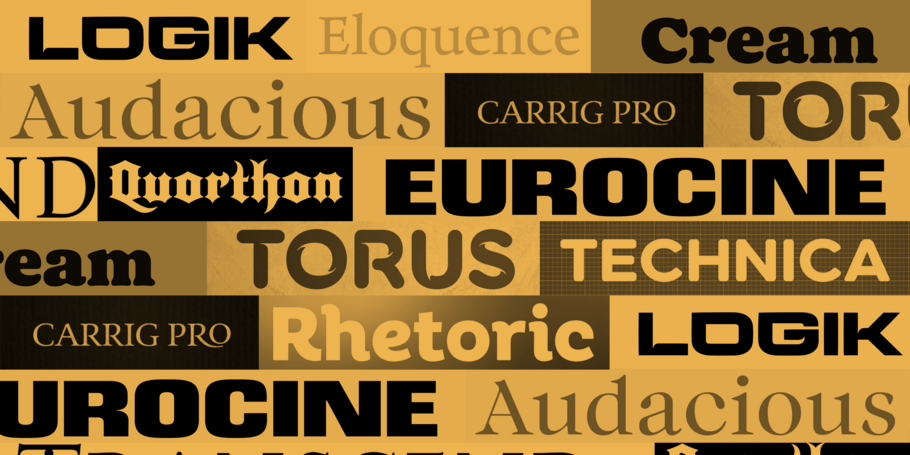
Paulo Goode.
Paulo Goode est un designer indépendant basé en Irlande, qui a adopté la création de caractères typographiques après une carrière de 30 ans dans l’illustration, le design graphique et le développement de sites web. Créée en 2016, sa fonderie a déjà publié plusieurs designs populaires, et ses polices ont été utilisées sur des emballages, dans des publicités pour des marques, pour des couvertures de livres et même dans des jeux vidéo. Les designs de Paulo consistent principalement en polices destinées aux supports commerciaux et à l’identité visuelle de marque, c’est-à-dire exactement le genre de typographie qu’il recherchait lorsqu’il était designer graphique. Il est spécialisé dans la création de types polyvalents bourrés de fonctionnalités qui apportent une valeur exceptionnelle à leurs utilisateurs.
Cream
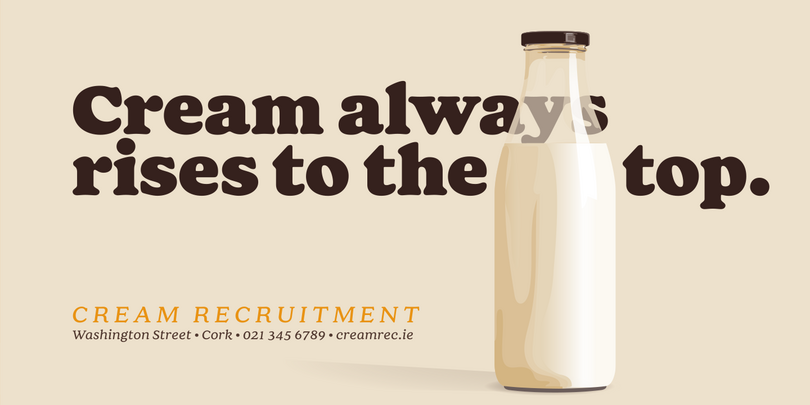
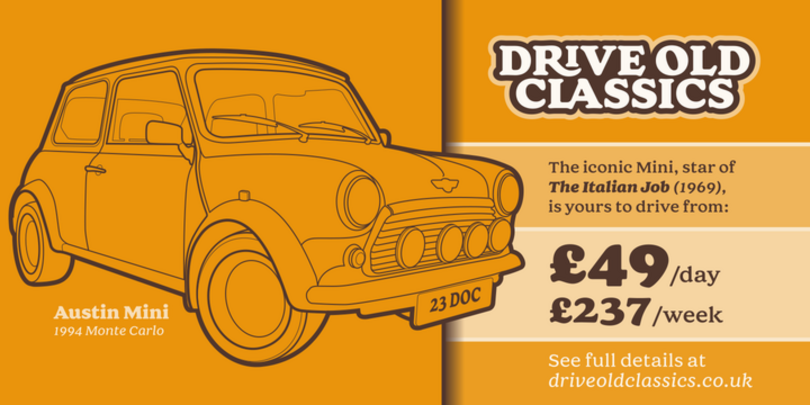
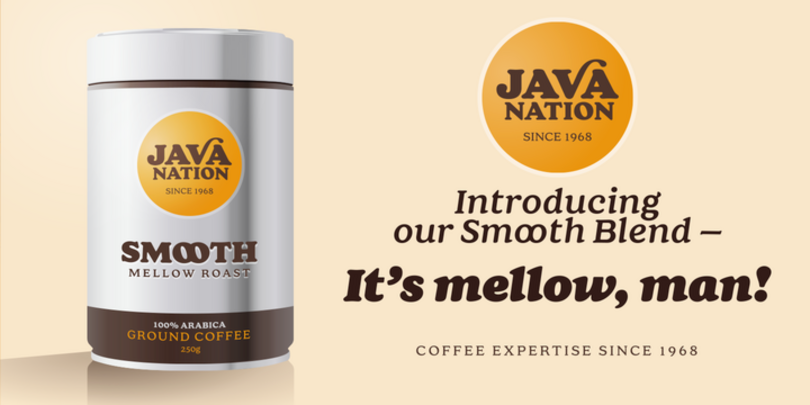
Cream est une police rétro douce à empattement, dotée de nombreuses alternatives et ligatures décoratives qui enrichiront vos compositions typographiques de fioritures distinctives. Utilisés subtilement, ces ornements et combinaisons de glyphes ajouteront du style et de la personnalité à vos créations. Bien que Cream soit parfaite pour le titrage et l’identité visuelle de marque, sa gamme de graisses et sa lisibilité intrinsèque en font une famille de polices qui convient à la plupart des applications, de l’identité de marque au corps de texte. Elle inclut 12 fontes et un jeu de caractères complet qui couvre toutes les langues latines d’Europe.
Logik
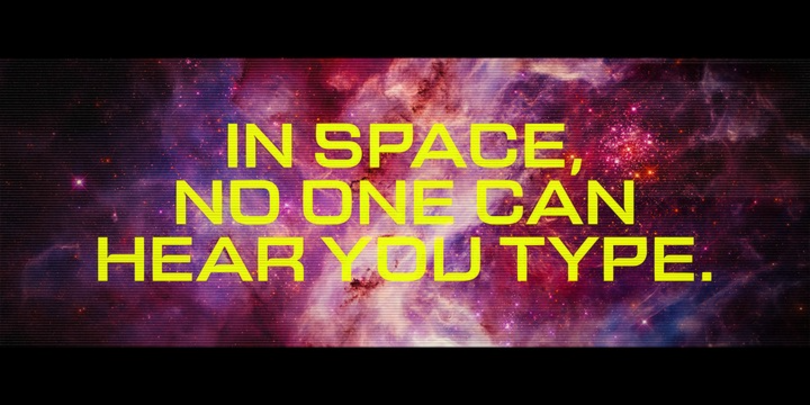
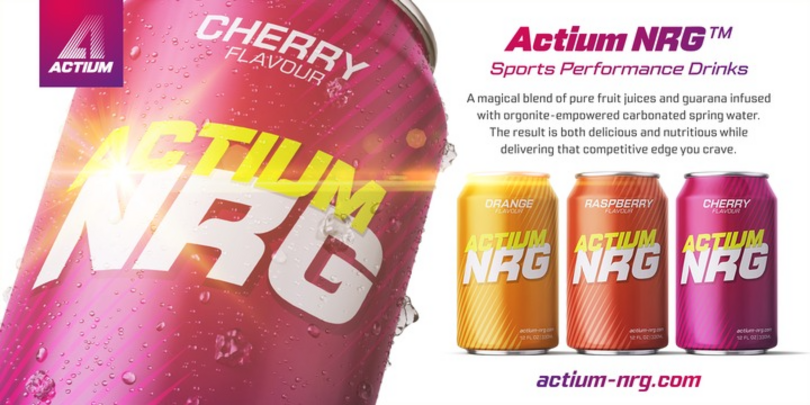
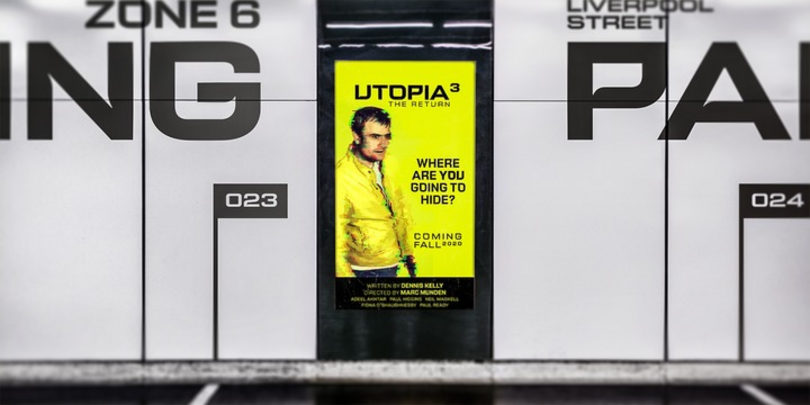
Logik est une police sans serif géométrique et futuriste. Sa personnalité est définie par des angles droits là où l’on attendrait plutôt des arrondis, ces contours nets conférant aux glyphes une certaine excentricité. Les pièges à encre gravés/stylisés bien évidés, alliés à des horizontales et à des verticales légèrement incurvées/effilées ajoutent une particularité à chaque forme de lettre. Ces subtilités se combinent pour donner à Logik une aura futuriste distinctive. Ce type est principalement utilisé pour les titres, les textes courts, l’identité de marque et les enseignes. Il s’avère idéal pour les titres de films et de livres ; c’est également une excellente option dans le domaine sportif ou des médias, ainsi que pour les projets typographiques dans l’univers du divertissement.
Carrig Pro
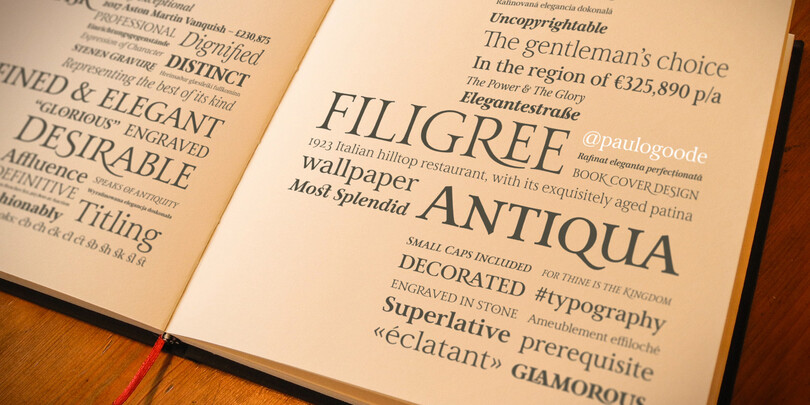
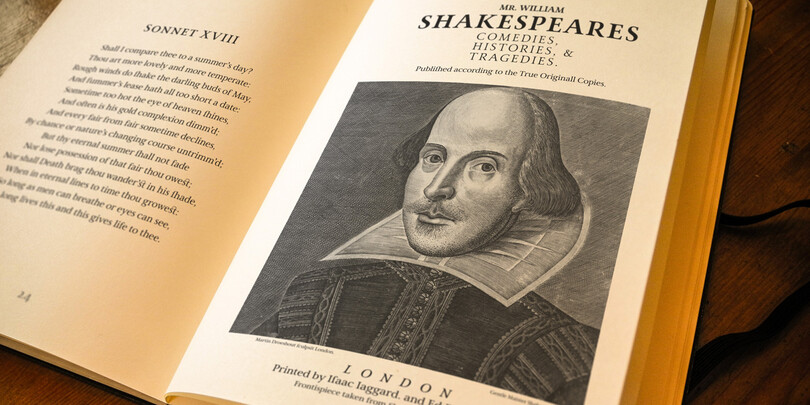
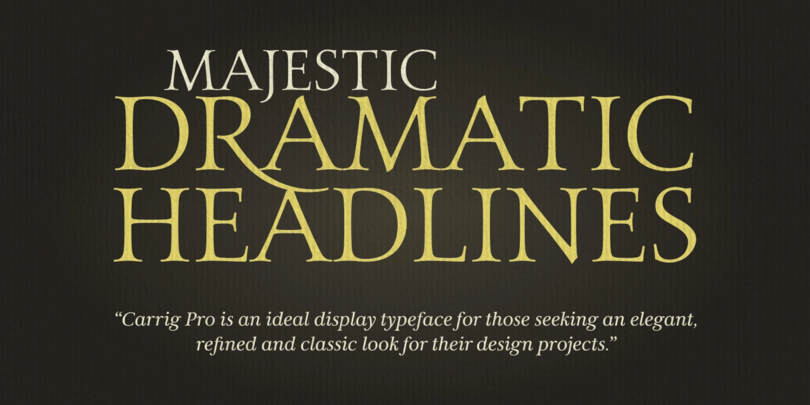
Carrig Pro est un type à empattement tout en raffinement et élégance. Classé dans la catégorie Antiqua, Carrig Pro est né de diverses influences allant des anciennes inscriptions romaines aux types de l’ère pré-moderne, ce qui lui confère son caractère si particulier. Carrig Pro est la police parfaite pour les designers cherchant à délivrer un message dans une esthétique distinctive et prestigieuse. Carrig Pro est une version étendue du type original Carrig. Elle possède de nombreuses fonctionnalités utiles pour les typographes, telles que de petites capitales faciles d’accès, des ligatures facultatives, des embellissements et des alternatives stylistiques, ainsi qu’un certain nombres de glyphes ornementaux.
Eponymous
Mécane dotée d’empattements imposants, bien découpés, Eponymous est une police slab polyvalente, stylée et contemporaine destinée à la création de logos et d’identités visuelles distinctives. Eponymous regorge de terminaisons en forme de boule et, sous des allures très rétro, elle offre bon nombre de fonctionnalités OpenType telles que des alternatives stylistiques, ainsi qu’un jeu complet de petites capitales incluant des signes diacritiques et des chiffres.
Transcend
Le type Transcend a été spécifiquement conçu pour le titrage et l’identité de marque. Cette police à 8 fontes uniquement composée de capitales est généreusement dotée de fonctionnalités OpenType, notamment des ligatures facultatives et des alternatives qui, lorsqu’elles sont employées subtilement, confèrent une note distinctive à la typographie des titres. Cette police est une émanation du type Carrig original créé par le designer. Elle est embellie par des lignes pures et des empattements nets, des pièges à encre stylisés, ainsi que des ornements, fioritures et ligatures minutieusement étudiés qui ajoutent classe et raffinement à chaque mot.
Quorthon
Quorthon est une collection de fontes de style gothique déclinée dans 3 variantes, qui présentent toutes un aspect plus contemporain et plus lisible que les polices gothiques séculaires standard. BLACK, la plus sévère des trois variantes, est dotée de barbes et d’éperons agressifs, lui conférant une stature imposante idéale pour faire passer un message puissant dans une identité visuelle, une enseigne ou un logo. DARK est une variante plus subtile, qui conserve les barbes mais y ajoute des empattements plus contemporains et des glyphes calligraphiques à fort contraste, au caractère affirmé et aux nuances raffinées. GREY, la plus douce des variantes Quorthon, offre un design minimaliste et des lignes nettes et droites, ce qui en fait une fonte idéale pour créer des titres et des en-têtes spectaculaires.
Technica
Type géométrique sans serif raffiné, Technica est une version plus conformiste de Meccanica, la famille de polices précédente. Si Technica conserve la structure de l’ancien type, les éléments hexagonaux sont plus effacés, les terminaisons chanfreinées sont aiguisées et une approche plus technique se dégage du peaufinage de chaque glyphe pour optimiser la performance et l’esthétique.
Eurocine
Eurocine est une police de titrage démonstrative, un type sans empattement aux formes carrées, parfait pour les titres, les logotypes et l’identité de marque. Cette police tente de capter l’atmosphère des génériques de films européens des années 70, notamment ceux du mouvement Giallo. En termes de style, Eurocine se situe entre le type Folio, de Walter Baum et Konrad Friedrich Bauer, et le type Eurostile conçu par Aldo Novarese, mais c’est une option plus polyvalente avec des petites capitales et des jeux stylistiques supplémentaires comprenant des ajouts de capitales, petites capitales (small caps et petite caps) et monocasse minuscules/majuscules.
Rhetoric
Rhetoric est une police de titrage humaniste et conviviale, à la personnalité marquée, idéale pour les projets d’identité de marque, les titres et les textes courts. Les fontes sont définies par leurs caractères romains que l’on pourrait décrire comme « italiques droits ». Le style traditionnellement associé à une police de caractères cursive a été appliqué ici aux glyphes romains. Rhetoric assume ses rondeurs, à l’instar des capitales voluptueuses A, M, U, V, W, X et Y, qui soulignent encore davantage la nature originale de cette police.
Eloquence
Eloquence a été créée afin de faciliter la lecture de textes longs. Elle est conçue pour être agréable à l’œil lors de la lecture de longs passages de texte. Inspirée des premières lettres imprimées de la Renaissance, cette police offre une esthétique moderne mâtinée d’une forte influence classique : elle utilise des caractéristiques contemporaines telles qu’une grande hauteur d’x, des panses et contreformes ouvertes, ainsi que des empattements et terminaisons d’une extrême précision. Avec son jeu complet de caractères latins, Eloquence est une police parfaite pour les documents imprimés comme les romans, les magazines et les rapports annuels, de même que pour leurs équivalents au format numérique.